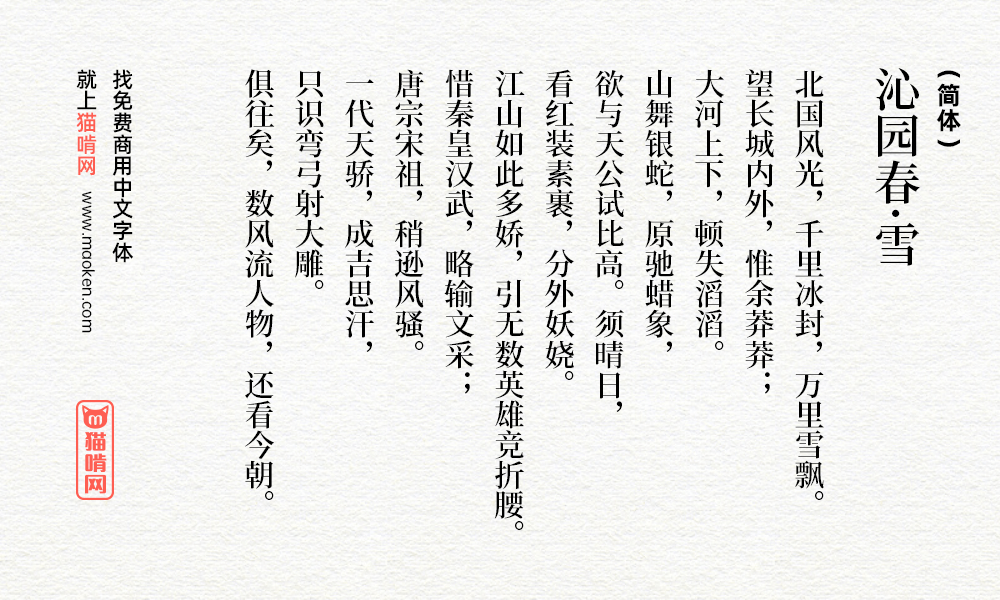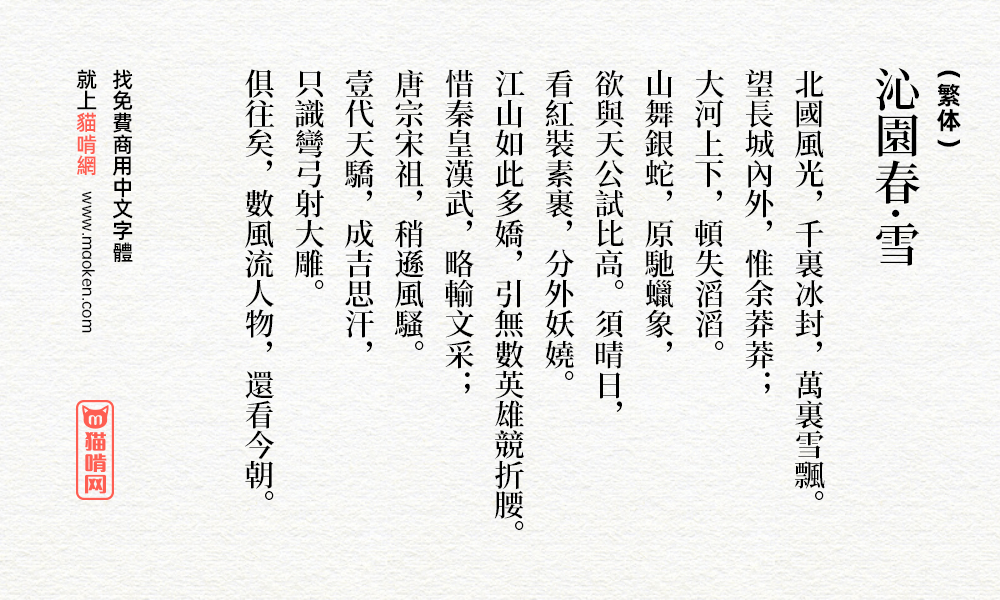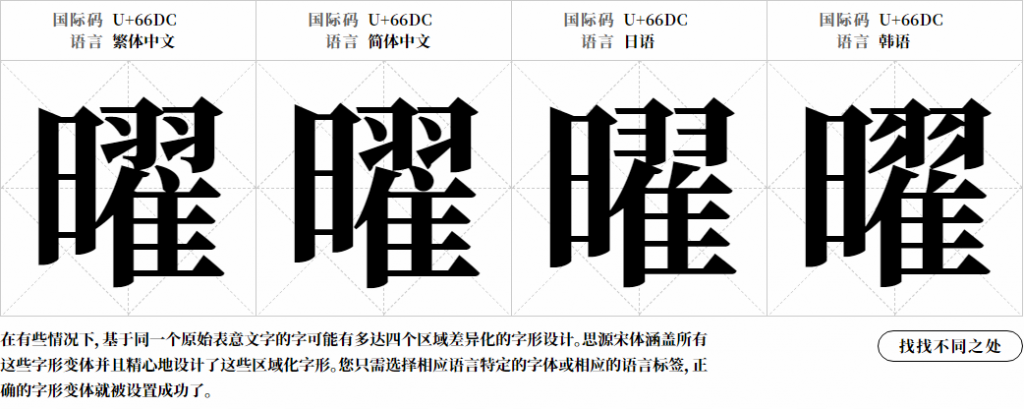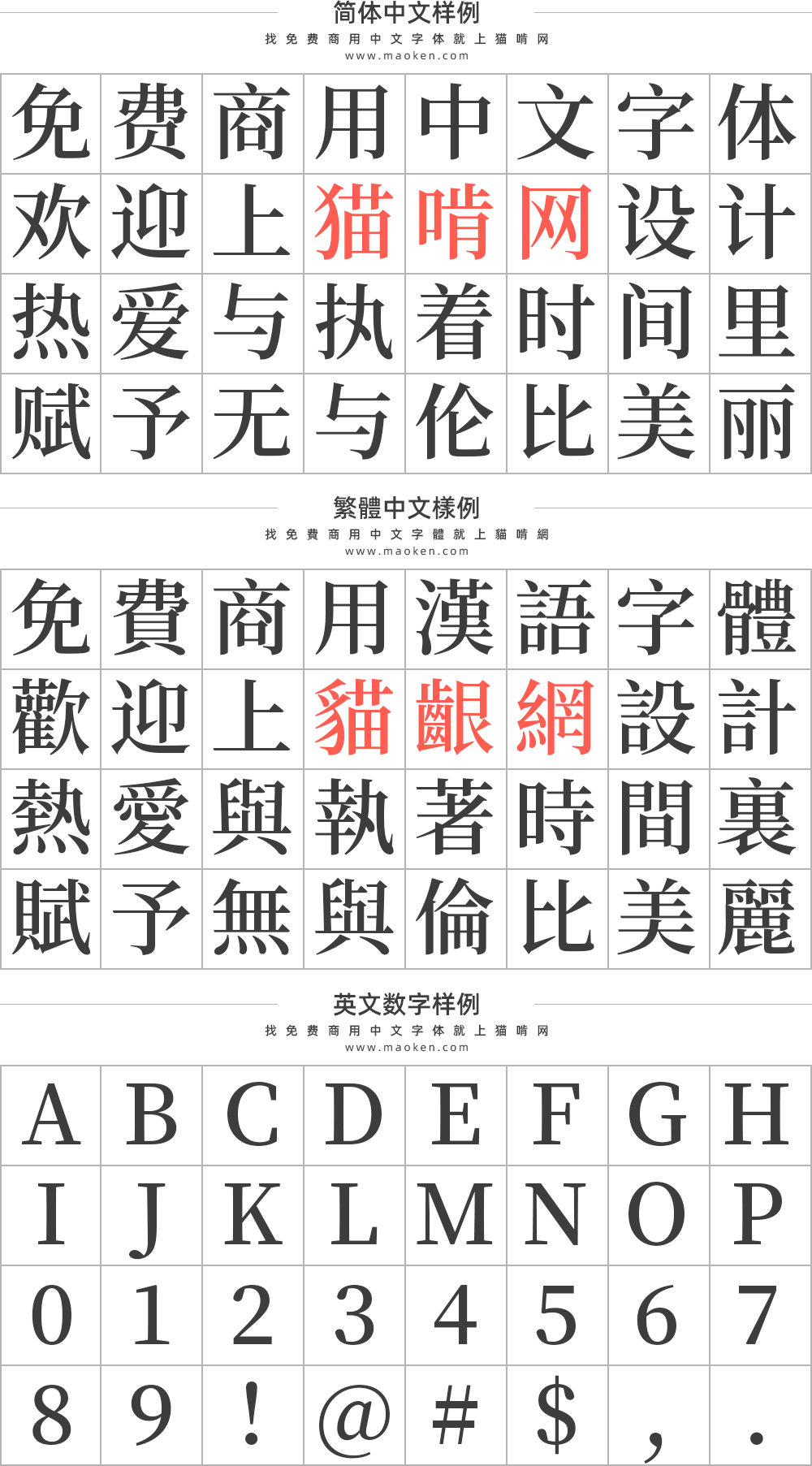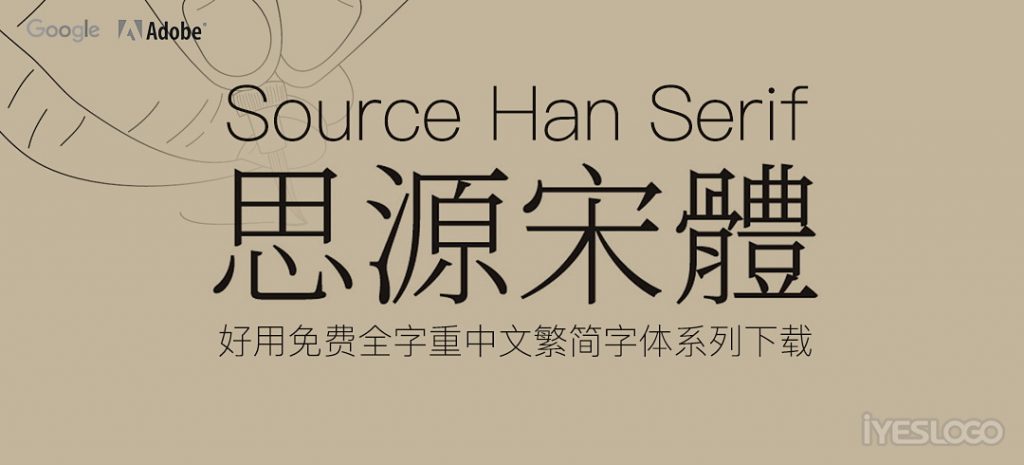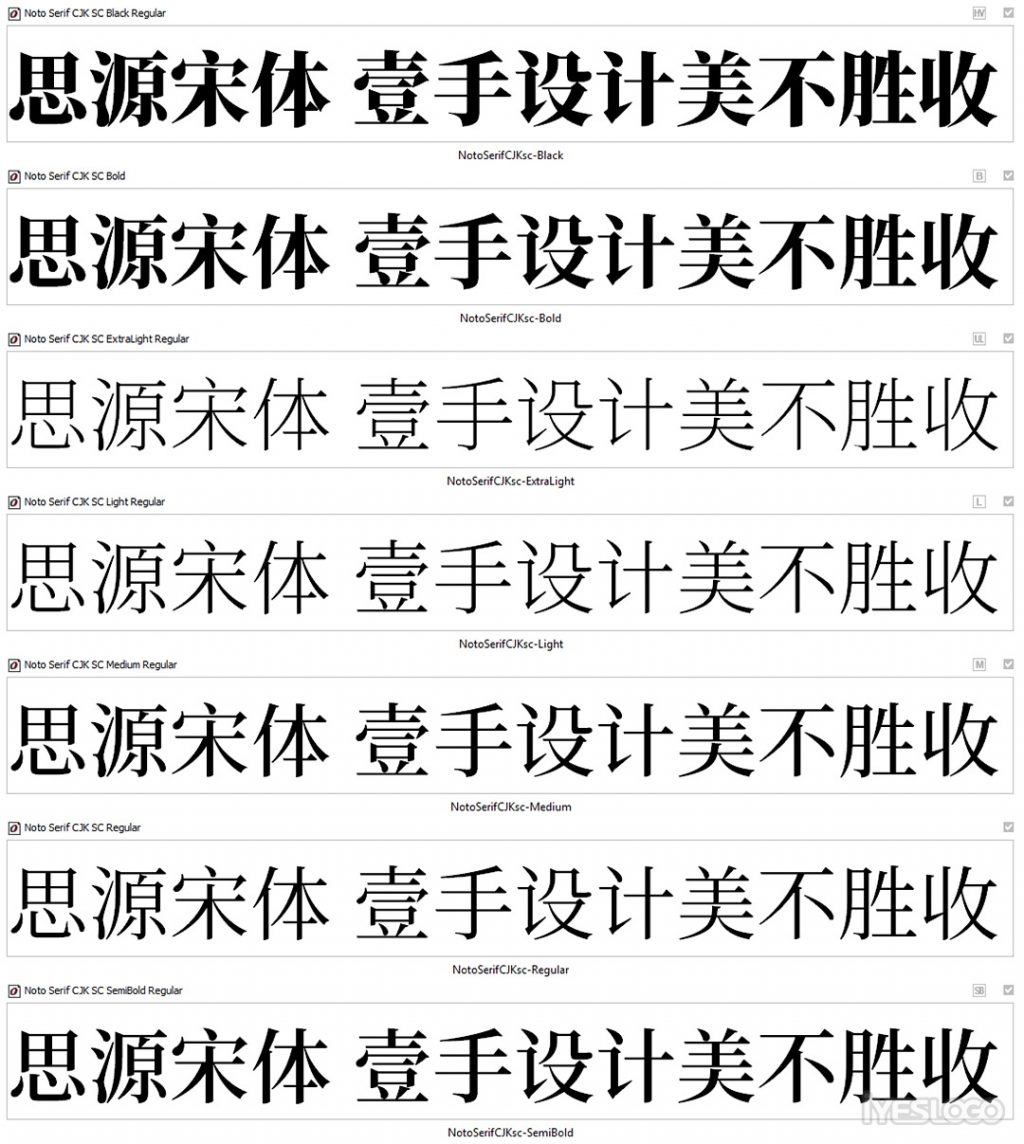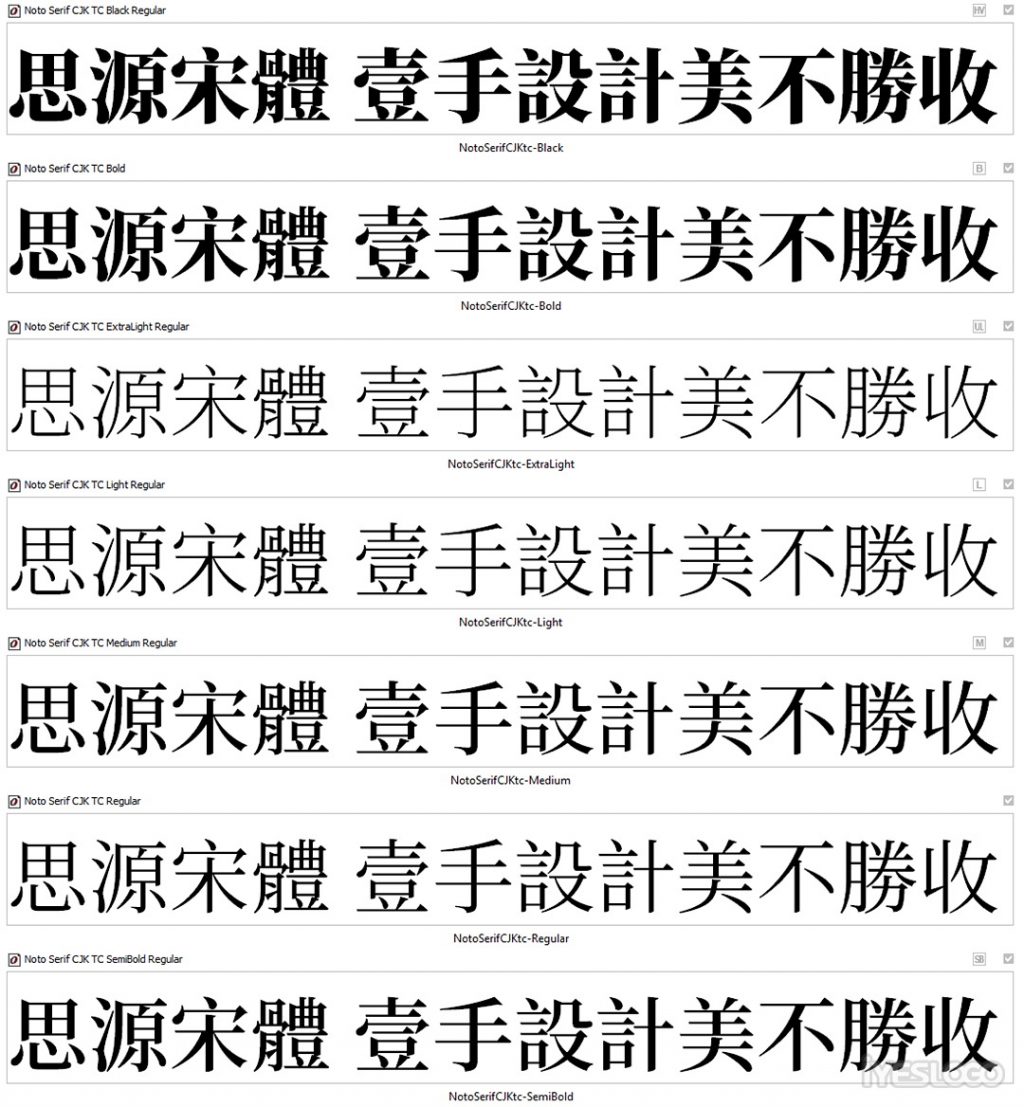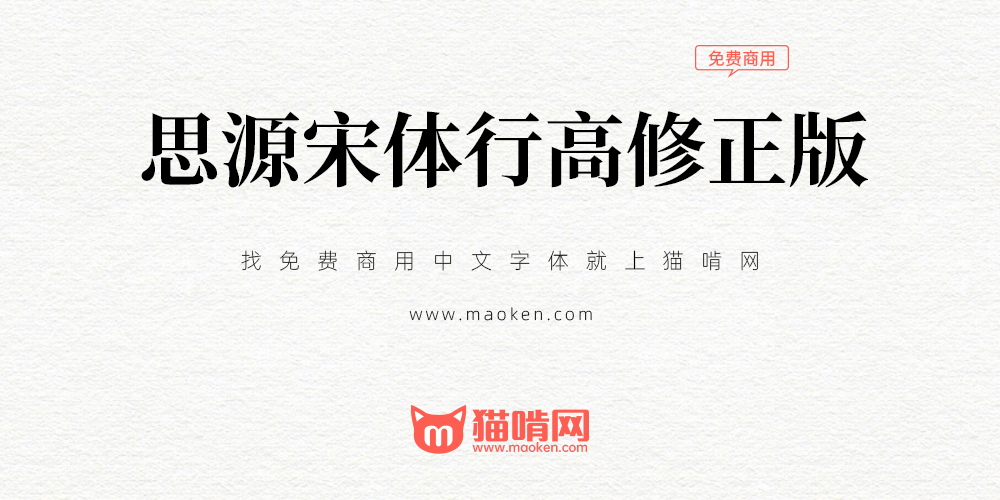
思源宋体:Adobe与谷歌开发的大名鼎鼎的免费商用字体
字体作者:Adobe & Google (美国) 字体字重:7个
思源宋体是Adobe Type发布的最新泛CJK字体,它是对应于思源黑体的宋体字体;作为思源黑体的兄弟字体,思源宋体支持四种不同的东亚语言(简体中文、繁体中文、日语和朝鲜语),7种粗细类型中的每一种都有 65,535个字形,可共同呈现一致的视觉美感。该字体还包含多个西方字形,支持拉丁语、希腊语和西里尔文字,这些字形均来源于 Source Serif。
经历了1年半开发,思源宋体(Source Han Serif)主旨在于为了与思源黑体进行搭配,该款字体同样是免费可商用。
思源宋体有两个版本,一个是Adobe发布的版本,一个是谷歌发布的版本。这两个版本有什么不同呢?
1、字体名称不同
这两个版本的区别是字体的名称不同。Adobe版本在PS中显示的字体名称是“思源宋体”,而谷歌版本在PS中显示的字体名称是“Noto Serif CJK”
关于本站提供的思源宋体行高修正版
官方上的思源宋体在中文字体的行高上显示有点问题,站酷设计师@wingsky82在2016年12月01日发布了一个以思源宋体1.001版本修正行高问题的思源宋体。具体的详情可以点击这里查看。